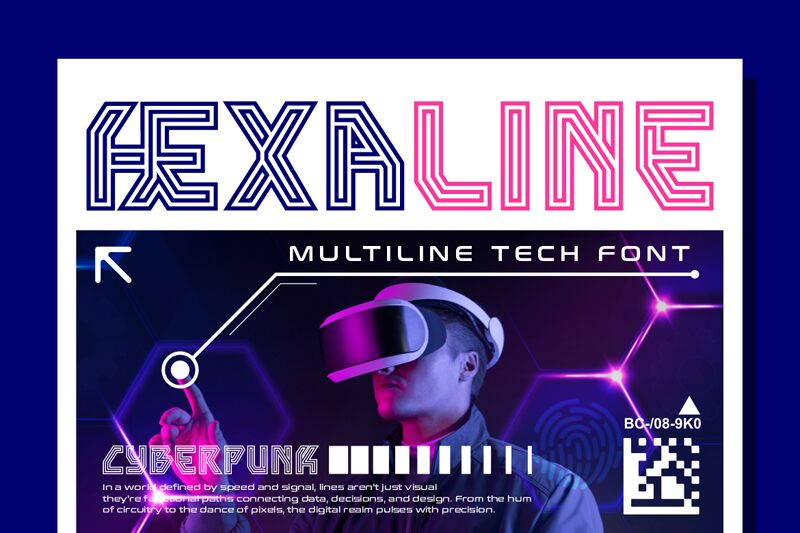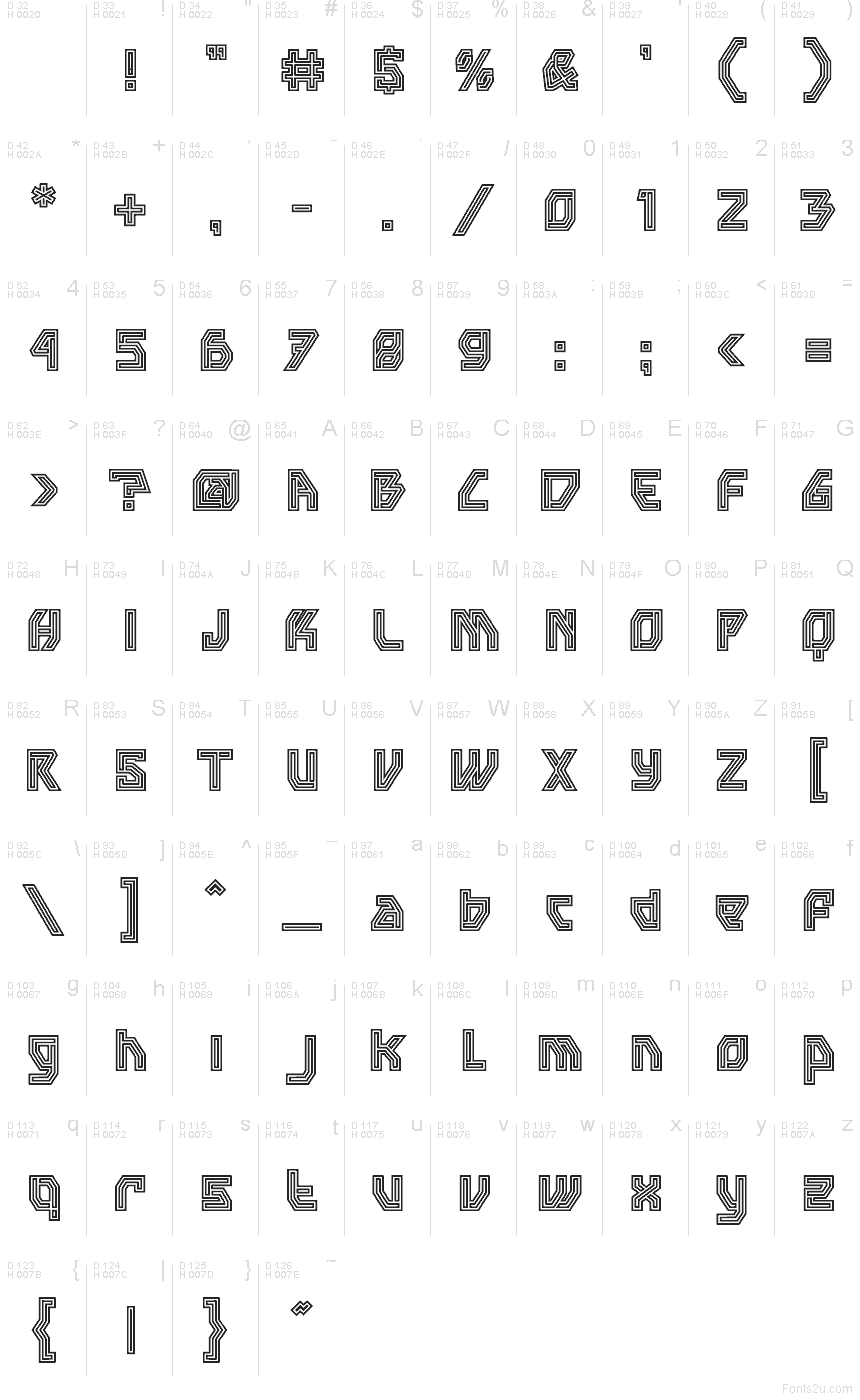
Hexaline de Shanaf Studio es una tipografía display techno gratuita con un aire de placa de circuito impreso. Las letras están construidas a partir de líneas paralelas repetidas y ángulos afilados, otorgando a las mayúsculas un ritmo tipo laberinto que se siente geométrico, futurista y, a la vez, con un toque retro informático.
Esta fuente gratuita es ideal para titulares de carteles, branding de juegos, portadas de música, tarjetas de título y gráficos de eventos tecnológicos donde su construcción a rayas puede destacar por sí misma. También funciona muy bien para logotipos cortos o monogramas, ya que el motivo de líneas repetidas hace que incluso unas pocas letras parezcan un sistema visual completo.